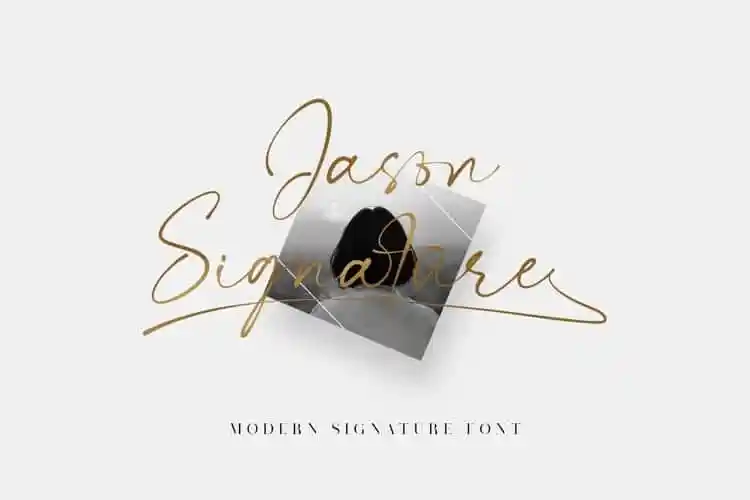
A “Jason Signature Font” é uma nova adição à categoria dos tipos de letra script modernos que irá revolucionar seu design. Criada especialmente para os desafios de criação atual, essa fonte traz um toque moderno e elegante ao seu trabalho. Ela foi projetada pela equipe fantástica da 99designs e apresentada pelo designer @lemonthe. A sua natureza fluida e sofisticada faz com que seja perfeita para uma variedade de aplicativos, desde criação de logotipos e identidades empresariais até design de convites e postais. Também é ideal para trabalhos criados especialmente para a internet como publicações nas redes sociais, anúncios ou conteúdo digital geral. Além disso, “Jason Signature Font” será sua melhor aliada em criações de embalagens para produtos, identidade visual, etiquetas, para um trabalho fotográfico ou até mesmo design de água-marinhas especiais. Com uma aparência elegante e versátil que se adapta a qualquer projeto, a Jason Signature Font é a escolha ideal para aqueles que desejam criar designs profissionais e impactantes. A sua fluida escrita garante um resultado único que vai marcar seu trabalho como especializado. Tudo isso em uma tipografia que é perfeitamente adequada para os mais diversos ambientes de design, tornando-se uma fonte indispensável para qualquer designer ou criador de conteúdo.